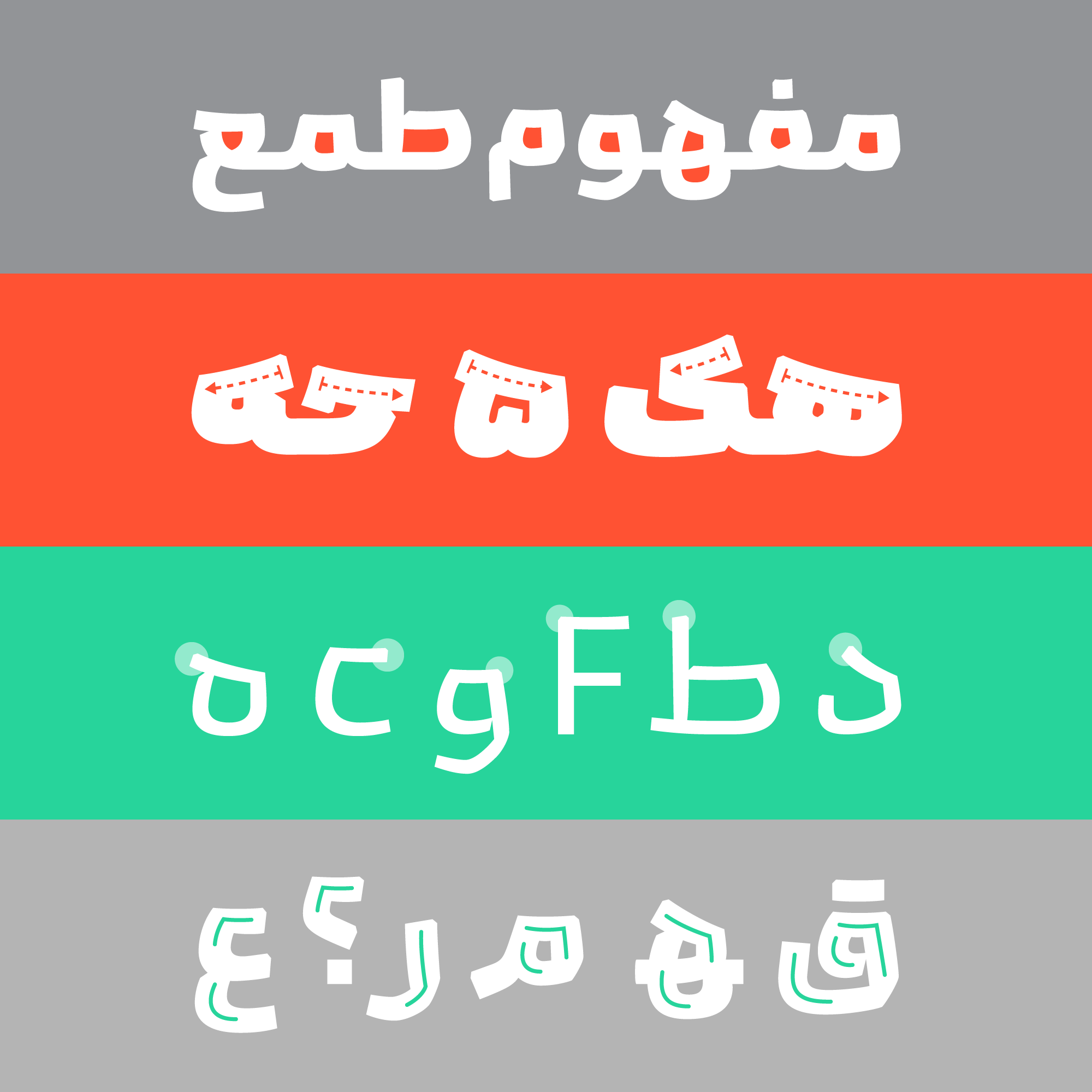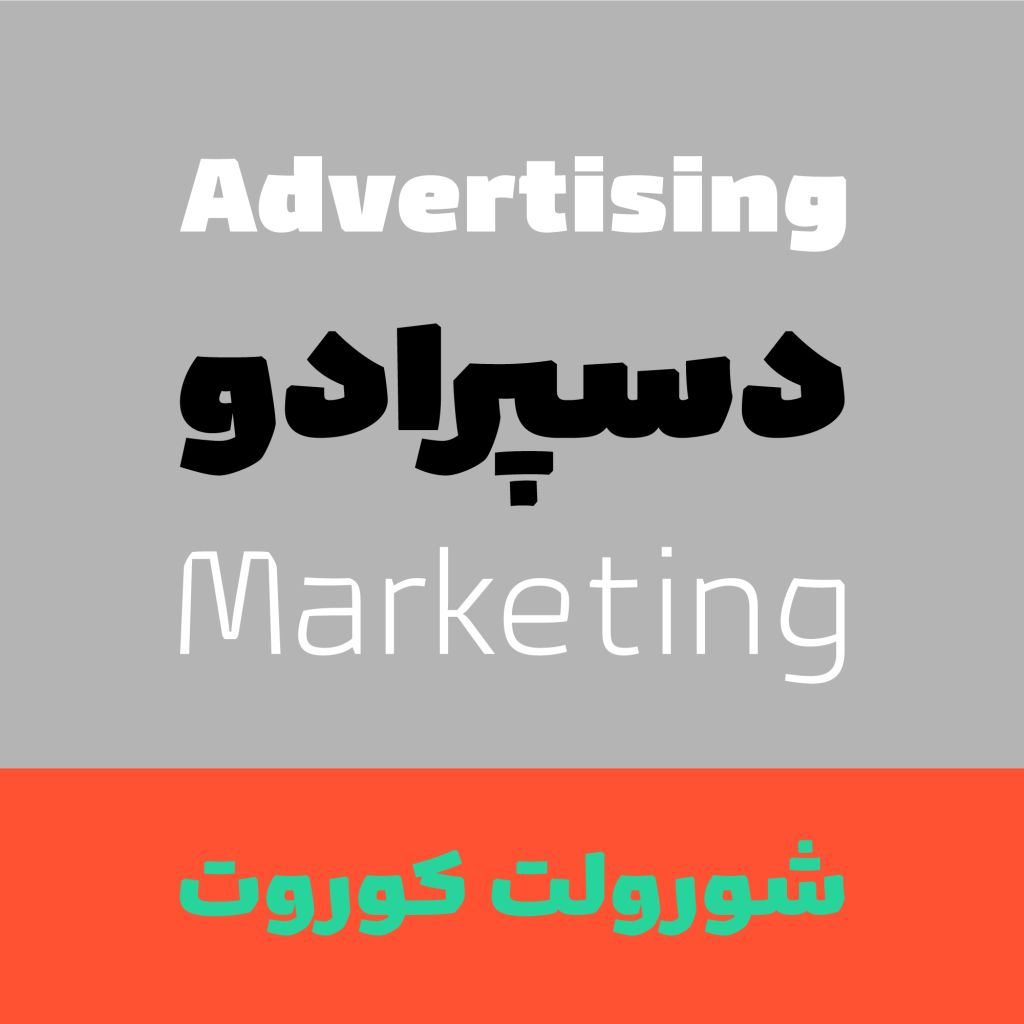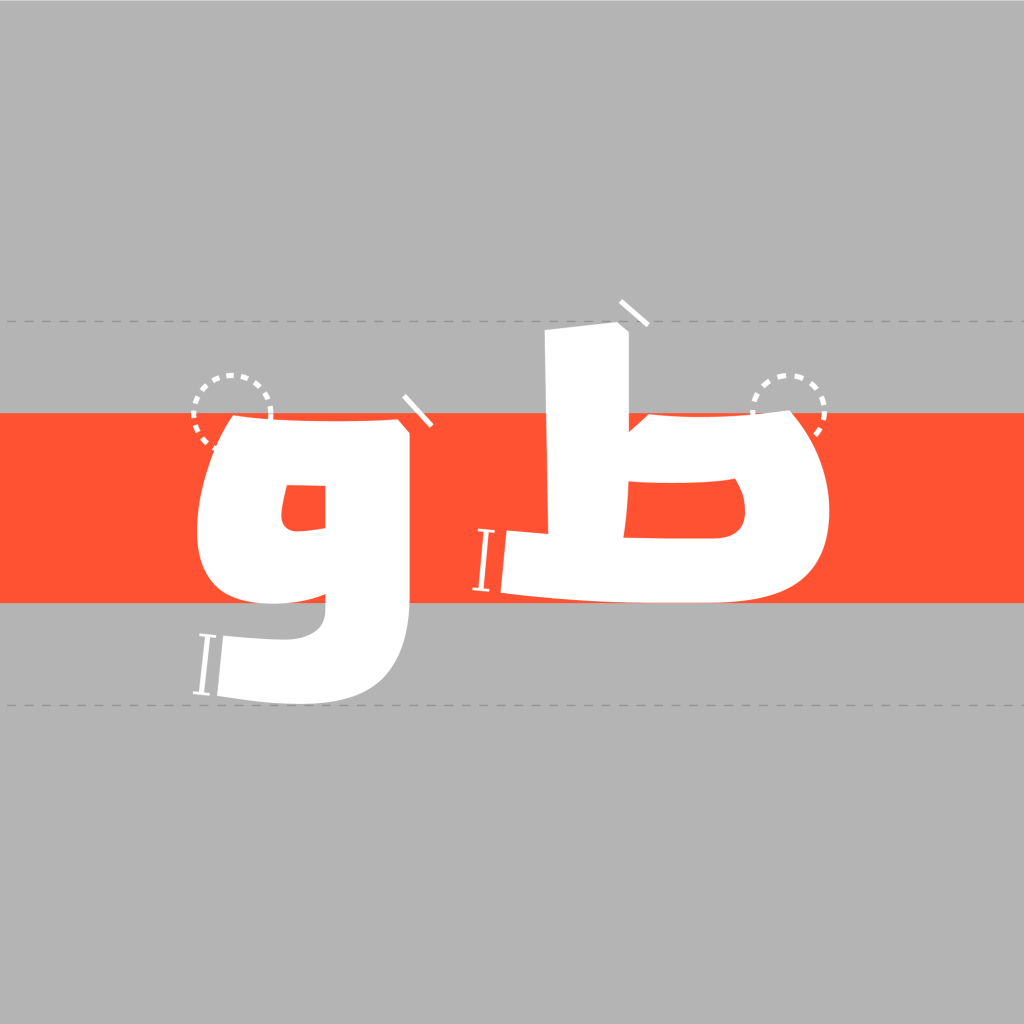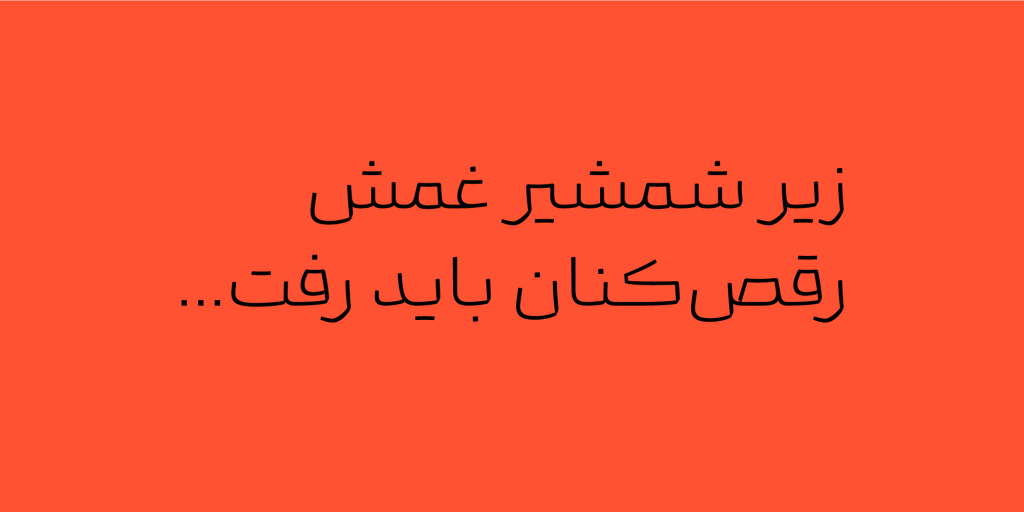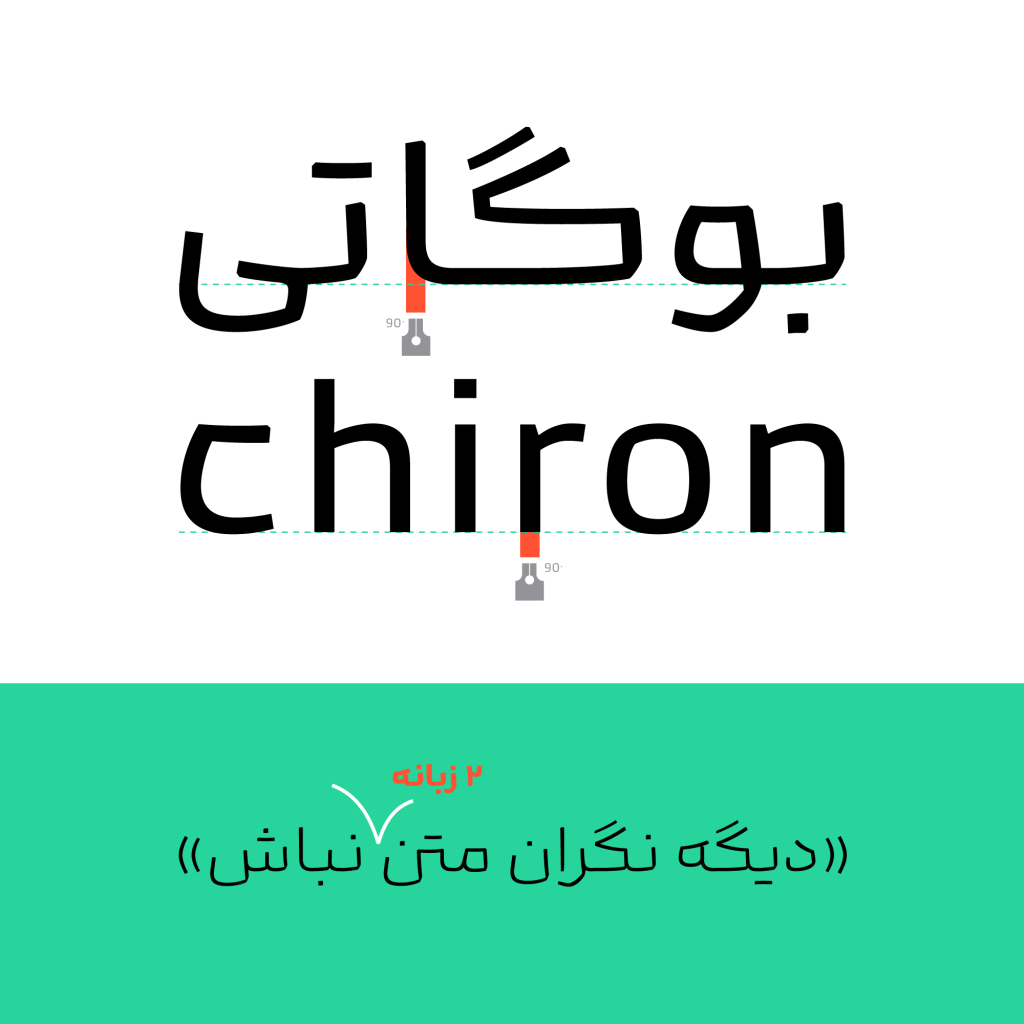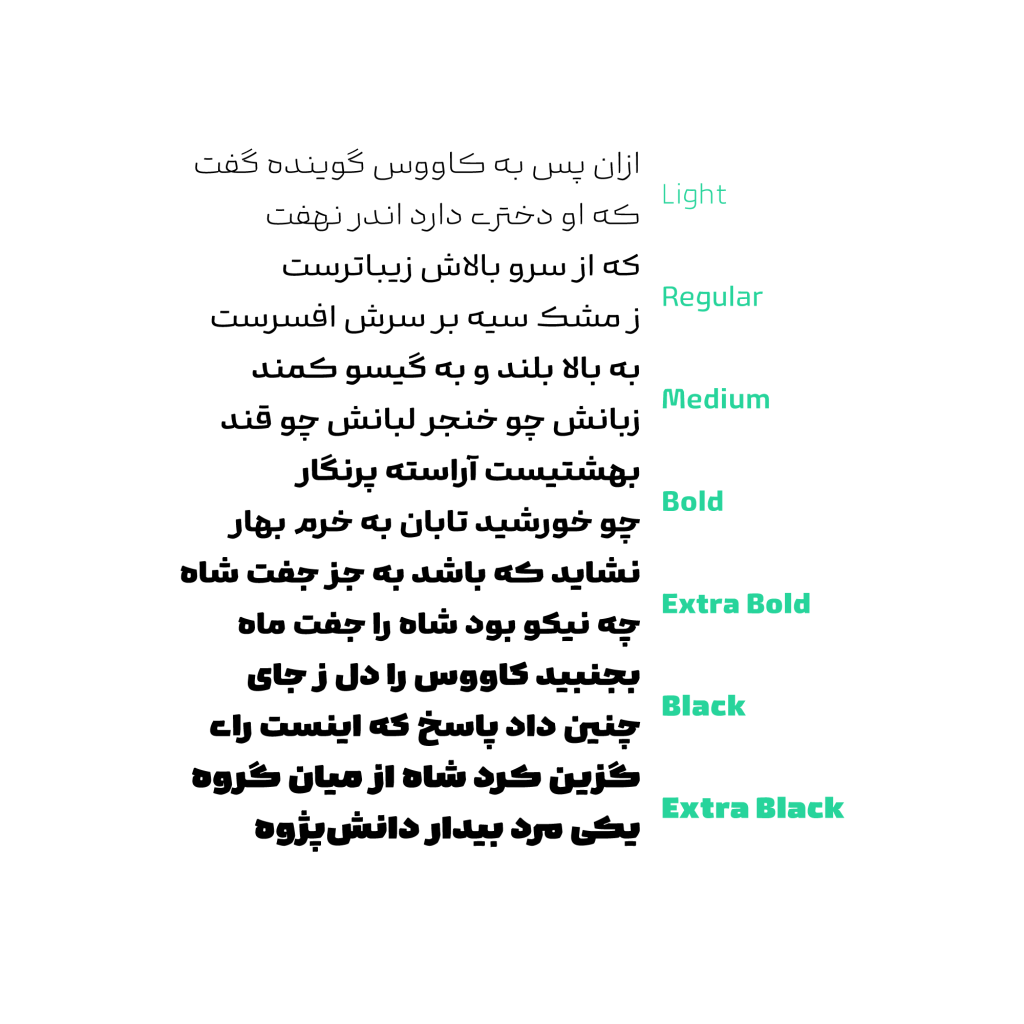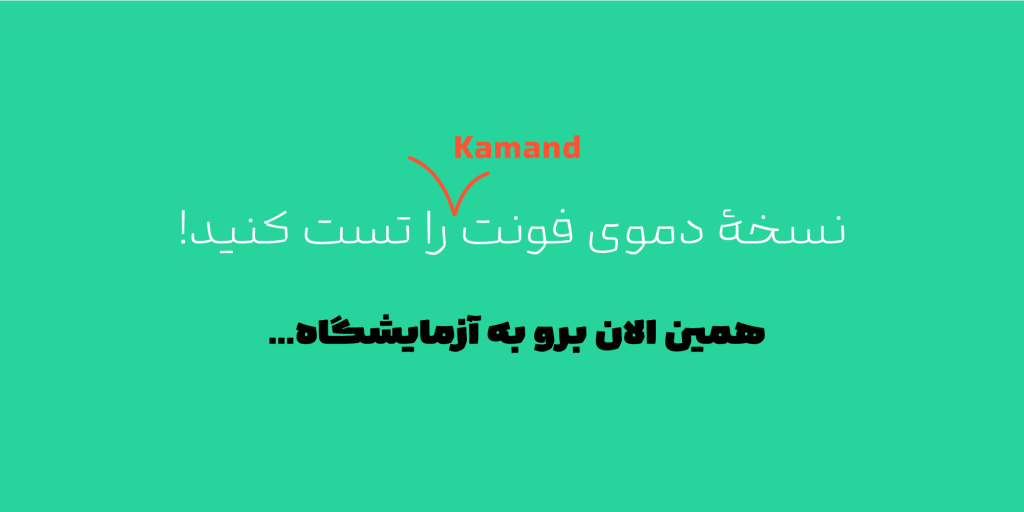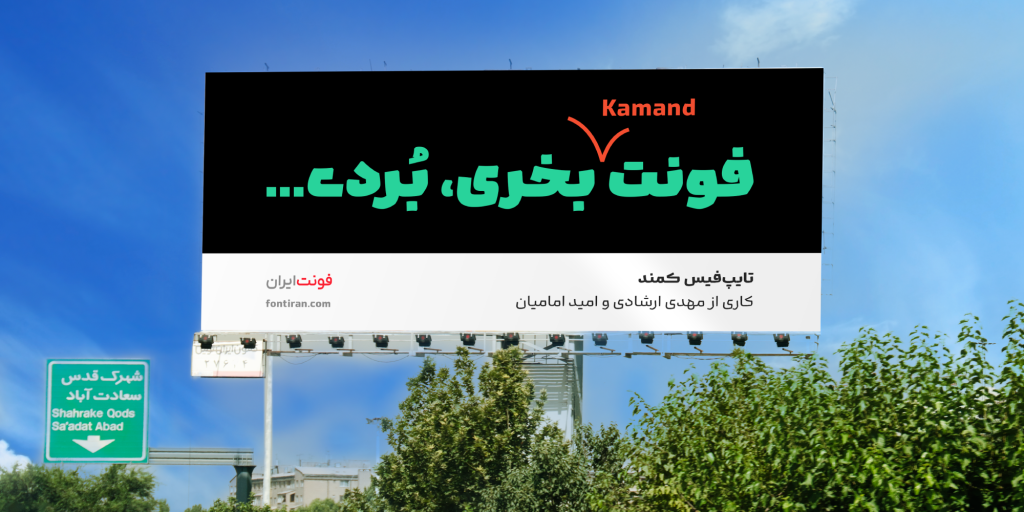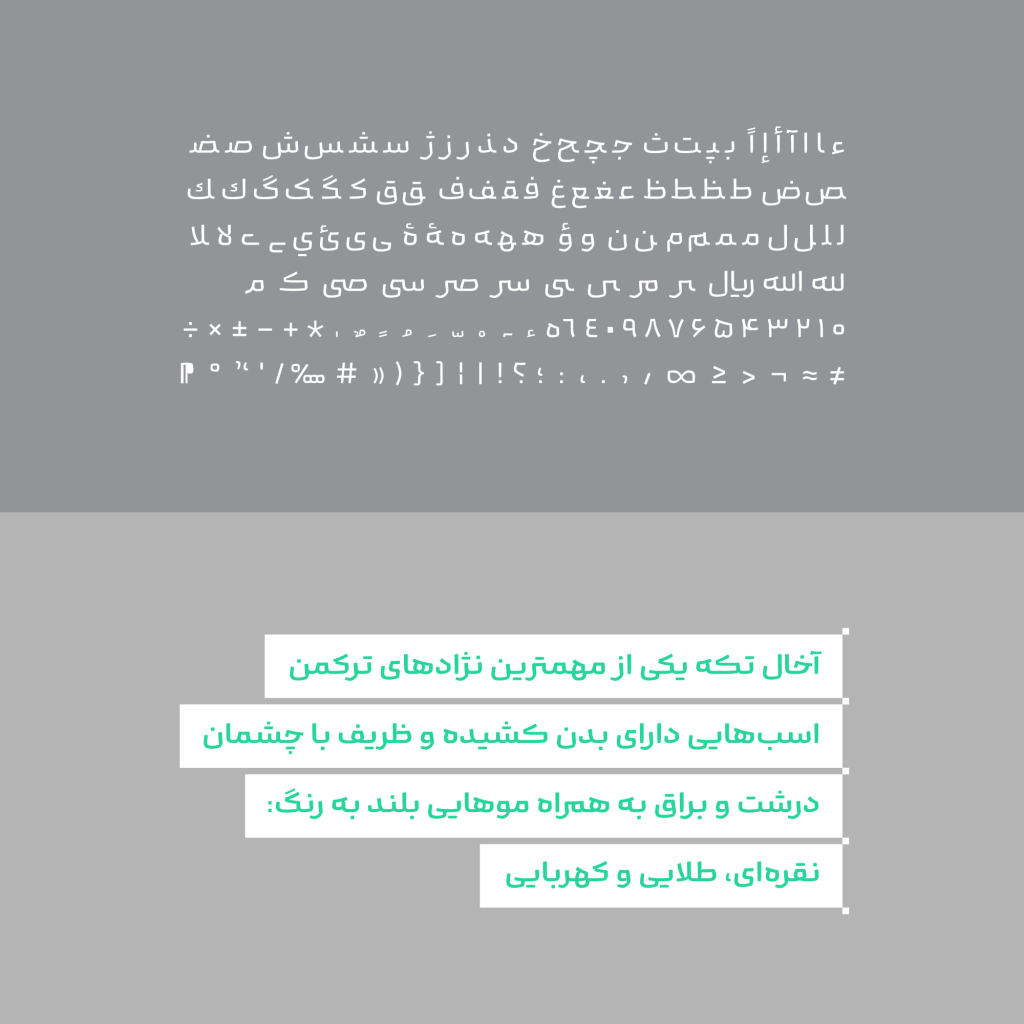
فونت کمند مناسب تبلیغات شما
فونت کمند قلمی ویژه و خاص که نسبت به رقبایش دارای تفاوتی شگرف و پویای است. تقریبا می توان گفت یکی از کاربرد های عمده کمند برای تبلیغات می باشد . از پوستر ها جلد کتاب ها و مجلات و بیلبورد ها گرفته تا دنیای وب و دیجیتال ازجمله پست ها و استوری های شبکه های اجتماعی پادکست ها و … این قلم، لحن آشنا و در عین حال متمایزی را به نوشتارهای تبلیغاتی اضافه میکند .
در طراحی کمند حروف زبان انگلیسی طراحی گردیده تا با خیال راحت متن های دوزبانه خود را در نرم افزار های طراحی از جمله آدوبی ایلسترتور فتوشاپ و یا حتی اینشات پیاده سازی کنید. از جنبه فرم های ساختاری و شخصیت می توان کمند را به مانند اسبی رام نشدنی و سرکش قلمداد کرد. که چموش و دلفریب است که با هر شلاقی رام نشده و سوارش را غافلگیر میکند.
همانطور در پاراگراف بالا گفته شده ویژگی غافلگیر کننده و دور از انتظار دارد و در جزئیات غیر قابل انتظار و پرهیجان است؛ این هیجان و جذابیت فرمی کاملا آگاهانه انتخاب شده و جزء جدا نشدنی تبلیغات امروز است. هر کاراکتر و هر حرکتی از جایی که انتظارش را نداریم یا برش میخورد یا میشکند و یا خلاف جهت میچرخد. این جذابیت و مزیت منحصر به فرد کمند است
ارتفاع خطوط کرسی یا صعود ها و نزولها در این تایپ فیس نزدیک و کوتاه است . این مدل طراحی کمک میکند تا جذابیت تایپفیس در تبلیغات محیطی و فضای مجازی بالاتر برود و تاثیر گذاری خاصی بر خوانندگان دارد.
کمند حس و حالی امروزی و نو دارد همچنین زنده و پویا بودن آن است . به همین دلیل با مخاطبین جوان دوست و همراه و مناسب فضاهای جدید و به روز نیز می باشد. از نقطه نظر ویژگی های گفته شده و همچنین هم خانوادگی فونت محال بسیار نزدیک به این قلم می باشد.
تنوع زبانی و وزنی تایپ فیس کمند
این تایپ فیس دارای خانواده ای از 7 وزن مختلف است تا نیاز های طراحی را برای شما در سطوح مختلف مرتفع نماید. همچنین با طراحی حروف و لیگچرهای زبان های مختلف از جمله انگلیسی و عربی پشتیانی از سایر زبان ها را در کارنامه خود دارد .
حروف و ترکیبات جایگزین (Discretionary Ligatures)
ترکیبات و لیگچر های جایگزین علاوه بر زیبایی بخشیدن به طراحی سبب ایجاد تنوع و پویایی می شود. کمند با بهره بردن از این ویژگی به شما عزیزان امکانات لازم را ارائه می دهد تا در نرم افزار های طراحی از جمله ایلسترتور و فتوشاپ پویایی و تنوع بیشتری به نوشته ها و طراحی های خود دهید.